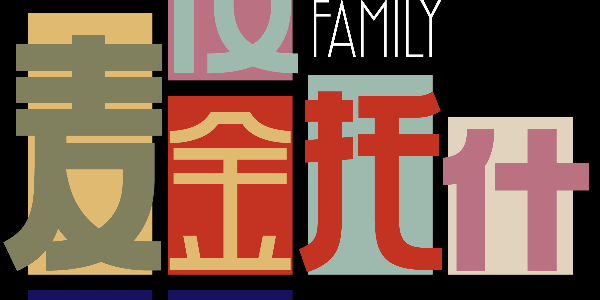
直线与几何碰撞的字体
查尔斯·雷尼·麦金托什(1868.6.7—1928.12.10),英国新艺术运动的思想领袖之一,在建筑和艺术领域留下了永恒的“麦金托什玫瑰”印记。
麦金托什的艺术风格根植于克莱德河畔的格拉斯哥,并融合了多重影响,在他的作品中,灵感源自苏格兰的本土文化,混合着新艺术运动的繁复精致和日本主义的简约形式。
把镜头再拉近些,就可以注意到出现在麦金托什建筑图稿中的手写字体,其特征是与麦金托什的建筑、家具设计语言一致的高直字形以及几何线条。这种风格独具的手写字体也应用于柳茶室等建筑中。
英国的字体设计师们当然不会忽略麦金托什风格独特的手写字体。在麦金托什的作品进入公有领域之后,对于麦金托什手写字体进行数字化诠释的字库接连出现在人们的视野中。
珠玉在前,英国的字体设计师们完成了对于麦金托什手写字体的还原和延续。但是,在遥远的东方,中国的字体设计师们有一个更为大胆的想法:在中文汉字中重现麦金托什的手迹。
2023 年,汉仪字库推出汉仪麦金托什家族,以中文字体设计重新诠释麦金托什的手写字体,将原手迹的高直几何线条作为语言,沟通中文汉字与拉丁字母,并且基于可变字体的原理拓展为总计 49 款字体的庞大家族,致敬这位英国新艺术运动的思想领袖。
汉仪麦金托什以原手迹高直而纤细的字形为原点,拓展至包含了 7 个字重(45-105)、7 种高度(H1-H7)总计 49 款字体的家族,其中包括保留了装饰方点的 6 款字体,高低粗细各不同,满足全面的排版需求。
字体的造型风格与麦金托什的建筑和家具设计风格高度一致,呈现出如同植物般垂直向上生长的状态。
整体由几何高直的造型和简约克制的曲线构成:
高度几何化的造型和对比强烈的直角在麦金托什的家具设计中得以体现。
弧度细致微妙的曲线灵感则来源于植物,著名的麦金托什玫瑰正是对于自然状态的学习。
汉仪麦金托什H7系列,是对于麦金托什手写字体还原度最高的系列,参考原手迹中的处理,将重心提高,笔画多集中于字形的上1/3部分,而在下方留白。
在5款字体(H7-45、H7-55、H7-65、H6-45、H6-55、H5-45)的中文字形中大胆延续了原手迹中的装饰方点,为保证字形的识读只在钩画中保留。
汉仪麦金托什家族的西文部分在还原麦金托什手迹的基础之上,进行了全新的设计,让百年之前的先锋得以延续,适应当代的审美及应用。
与麦金托什原手迹相同,有着高直而纤细的造型和夸张的x高度(x-height)。
大写字母造型风格强烈,小写字母造型则更为简约克制。
根据排版的需要,可以选择大写字母 O 的替代字形。
替代字形之外,还通过 OpenType 技术实现了 214 个大写字母自由连字字符,将复杂的装饰与简洁的形式融合,赋予排版丰富而多变的可能性。
对于不同字高和字重间的 LA 连字进行了突变设计,这一细节的处理使得连字的展示效果更为清晰。